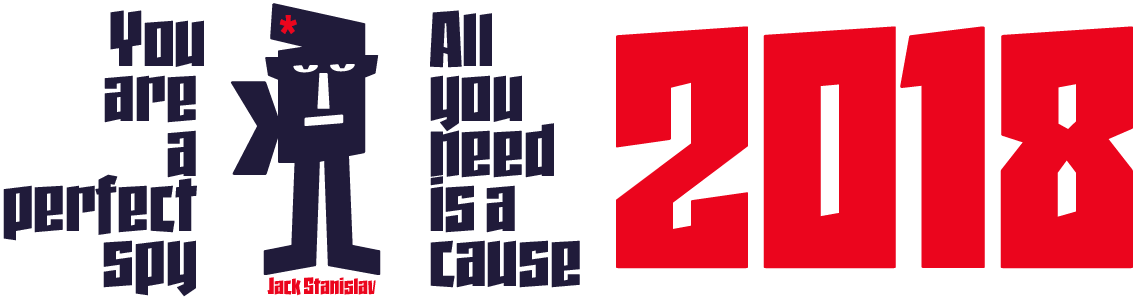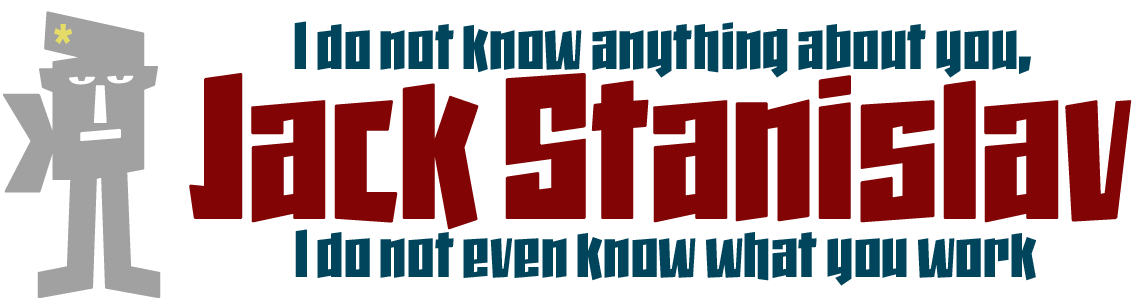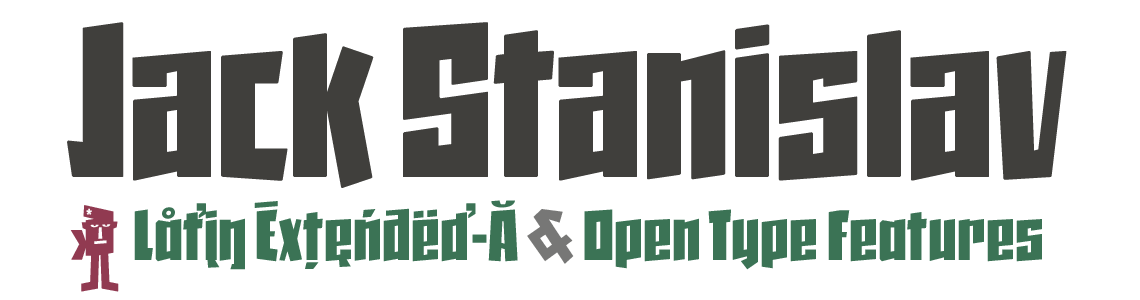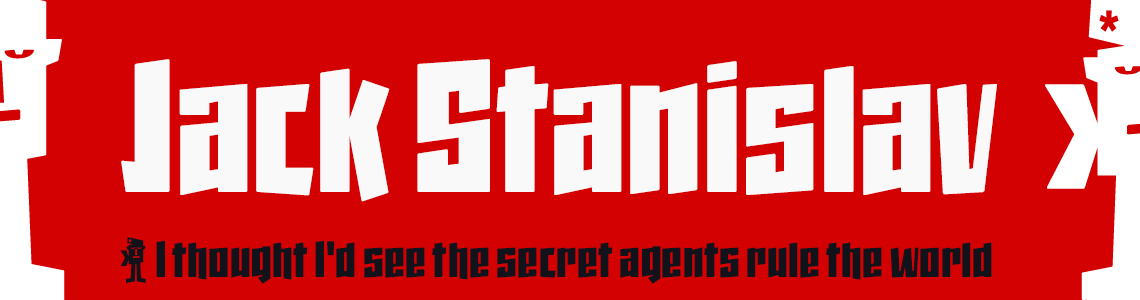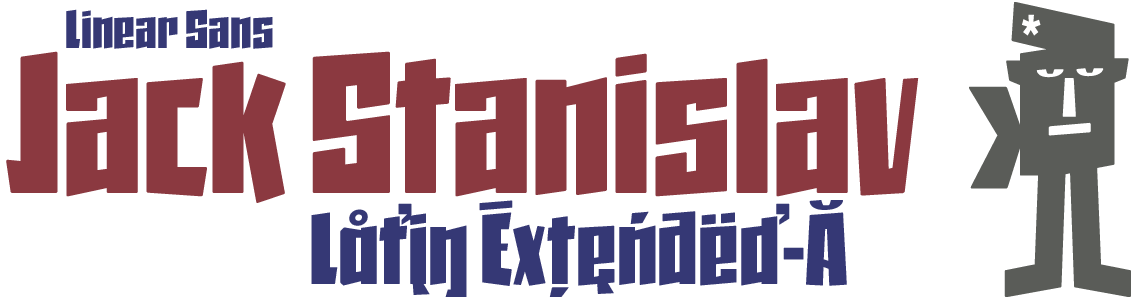
La inclinación superior de las letras, la combinación de formas horizontales con inclinadas, los cortos ascendentes y descendentes y el alargamiento inferior de algunas astas te permitirá imprimir estilos variados con mucho movimiento según el contexto del diseño.
Fun Condensed Typeface
Estilo: Sans, Neo-Grotesca, Display
Proporción: Extra condensada, Cuadrada
Comencé el dibujado de esta fuente con la intención de crear una nueva tipografía decorativa de estilo Blackletter pero modernizando los trazos, después de dibujar varias letras imitando el ductus de este tipo de fuentes intentando simplificarlos, surgió, todo el ADN de la actual Jack Stanislav, finalmente una tipografía sin Serif de trazos lineales que imitan el ángulo de una pluma gruesa.